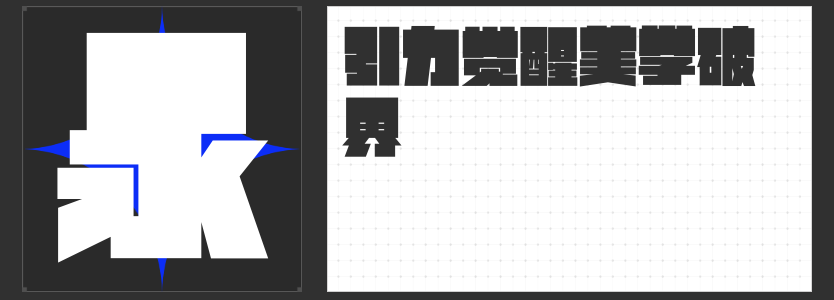
逆反差字体:打破常规的视觉张力美学
在字体设计的探索中,逆反差字体以其颠覆传统的笔画粗细对比与结构张力,成为当代设计中表达冲突感、戏剧性与现代性的利器。这类字体通过刻意强化局部笔画的粗细反差,打破“横细竖粗”的经典法则,在视觉上制造出动态的失衡与平衡,为品牌标识、海报标题、艺术创作等场景注入独特的个性语言。以下四款精心设计的逆反差字体,以各自的设计哲学诠释了这一风格的多元可能。
一、励字逆反差圆舞简 超级黑
这款字体以方正字型为基底,通过软硬兼备的笔画处理重新定义逆反差的视觉逻辑。其核心创新在于将撇、捺、钩及部分点笔画转化为饱满的弧线,在直线与曲线的碰撞中形成张力:直线部分延续黑体的理性秩序,弧线则赋予字体灵动的呼吸感。中宫的适度放大与重心的精准把控,确保了字体在夸张对比下的稳定性,而笔画的对称性设计则强化了视觉的仪式感。这种“刚柔共生”的特质,使其既能传递力量感,又不失优雅韵律。
二、励字造大头黑 超级粗
顶部加粗、底部纤细的颠覆性设计,是这款字体的标志性语言。通过极端化的笔画粗细对比,它构建出一种“头重脚轻”的视觉错觉,却因横平竖直的笔画与棱角分明的转折而保持了整体的平衡感。极度的夸张并未牺牲识别性,反而通过强化字型轮廓的厚重感,传递出强烈的存在感与冲击力。这种设计策略尤其适合需要突出权威感或戏剧性的场景,如品牌主标、活动主题等。
三、励字造逆反差踢踏
以直线与直角为核心,这款字体将逆反差的对比推向极致:顶部与底部笔画如楔形般厚重,中间笔画则纤细如丝,形成近乎断裂的视觉张力。中宫的宽阔布局与布白的均匀分配,确保了字体的可读性,而点笔画的灵活变形与对称处理,则赋予其几何抽象的美感。这种“极简中的极致对比”使其成为现代艺术、科技品牌等追求前卫表达的优选。
四款字体虽路径各异,却共同指向逆反差设计的本质——在冲突中寻找和谐,在失衡中构建秩序。它们以笔画为画笔,在传统与创新的边界上书写新的视觉语法,为设计师提供了突破常规、表达态度的工具。无论是追求优雅的弧线叙事、重量级的视觉宣言,还是极简的几何狂想,逆反差字体都能以独特的语言,让设计“活”起来。